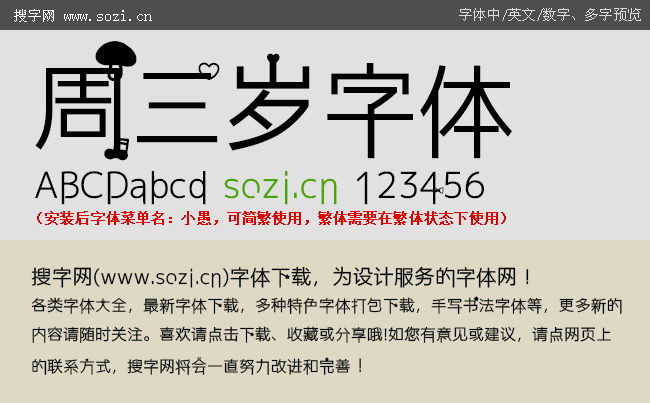
周三歲字體
搜字網(wǎng)給大家提供一款周三歲字體手機(jī)中文字體下載。這款手機(jī)字體是以黑體字體為原形,字體進(jìn)行了一些簡(jiǎn)單變化,筆畫間又嵌入了可愛(ài)的卡通圖案。具有黑體端正易認(rèn)的風(fēng)格,卡通味也特別濃,特別適合喜歡手機(jī)字體個(gè)性一些的朋友在手機(jī)上安裝使用。